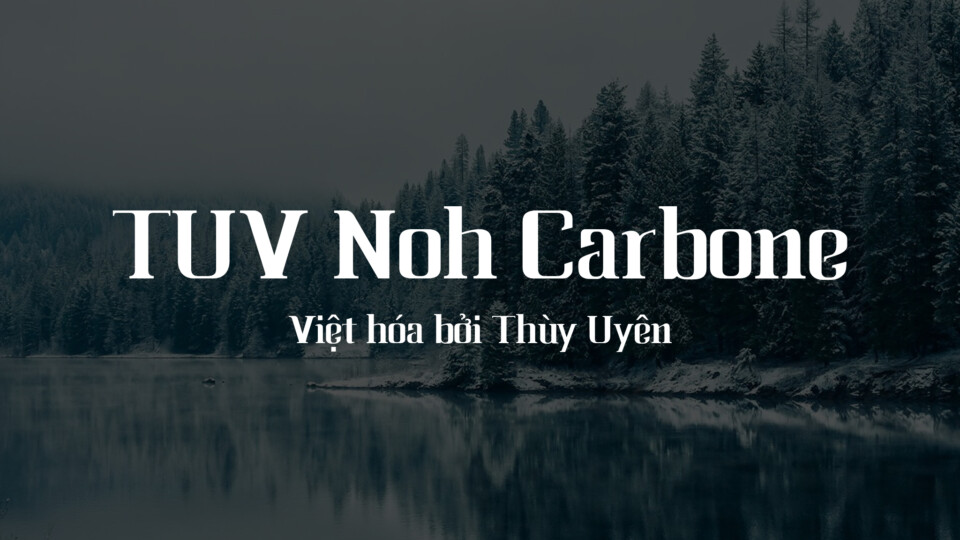
Font Việt hóa TUV Noh Carbone – Việt hóa bởi Thùy Uyên
Font Việt hóa TUV Noh Carbone – Việt hóa bởi Thùy Uyên – Sự kết hợp hoàn hảo giữa hiện đại và sang trọng
Trong thế giới thiết kế đồ họa, việc lựa chọn một bộ Font Miễn Phí chất lượng đóng vai trò quyết định đến thẩm mỹ của tác phẩm. Font Việt hóa TUV Noh Carbone – Việt hóa bởi Thùy Uyên là một ví dụ điển hình cho sự tinh tế, mang lại phong cách hiện đại và chuyên nghiệp cho người sử dụng. Được chăm chút kỹ lưỡng bởi designer Thùy Uyên, bộ font này không chỉ đảm bảo đầy đủ các dấu tiếng Việt mà còn giữ trọn vẹn tinh thần của bản thiết kế gốc.
Đặc điểm nổi bật của Font Việt hóa TUV Noh Carbone – Việt hóa bởi Thùy Uyên
Thiết kế tối giản và ứng dụng đa dạng
TUV Noh Carbone sở hữu các đường nét thanh mảnh nhưng vô cùng chắc chắn, phù hợp cho nhiều mục đích sử dụng khác nhau từ in ấn đến hiển thị kỹ thuật số. Người dùng có thể dễ dàng ứng dụng bộ font này trong việc thiết kế poster bài giảng, làm tiêu đề cho các dự án nghệ thuật hoặc trình bày tài liệu học tập một cách trực quan nhất. Font Việt hóa TUV Noh Carbone – Việt hóa bởi Thùy Uyên giúp các bạn học sinh và giáo viên tạo ra những nội dung thu hút mà không cần quá am hiểu về kỹ thuật đồ họa phức tạp.